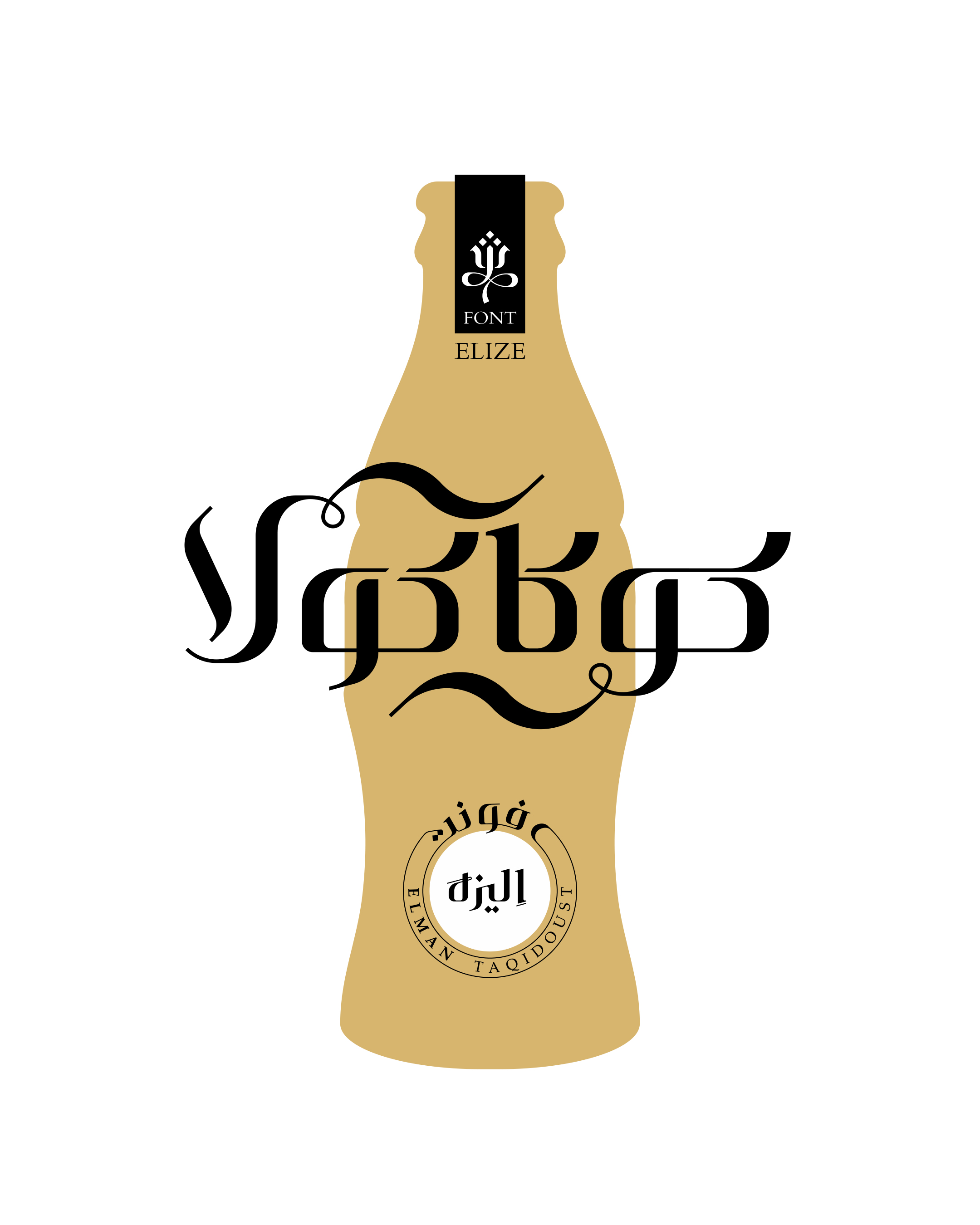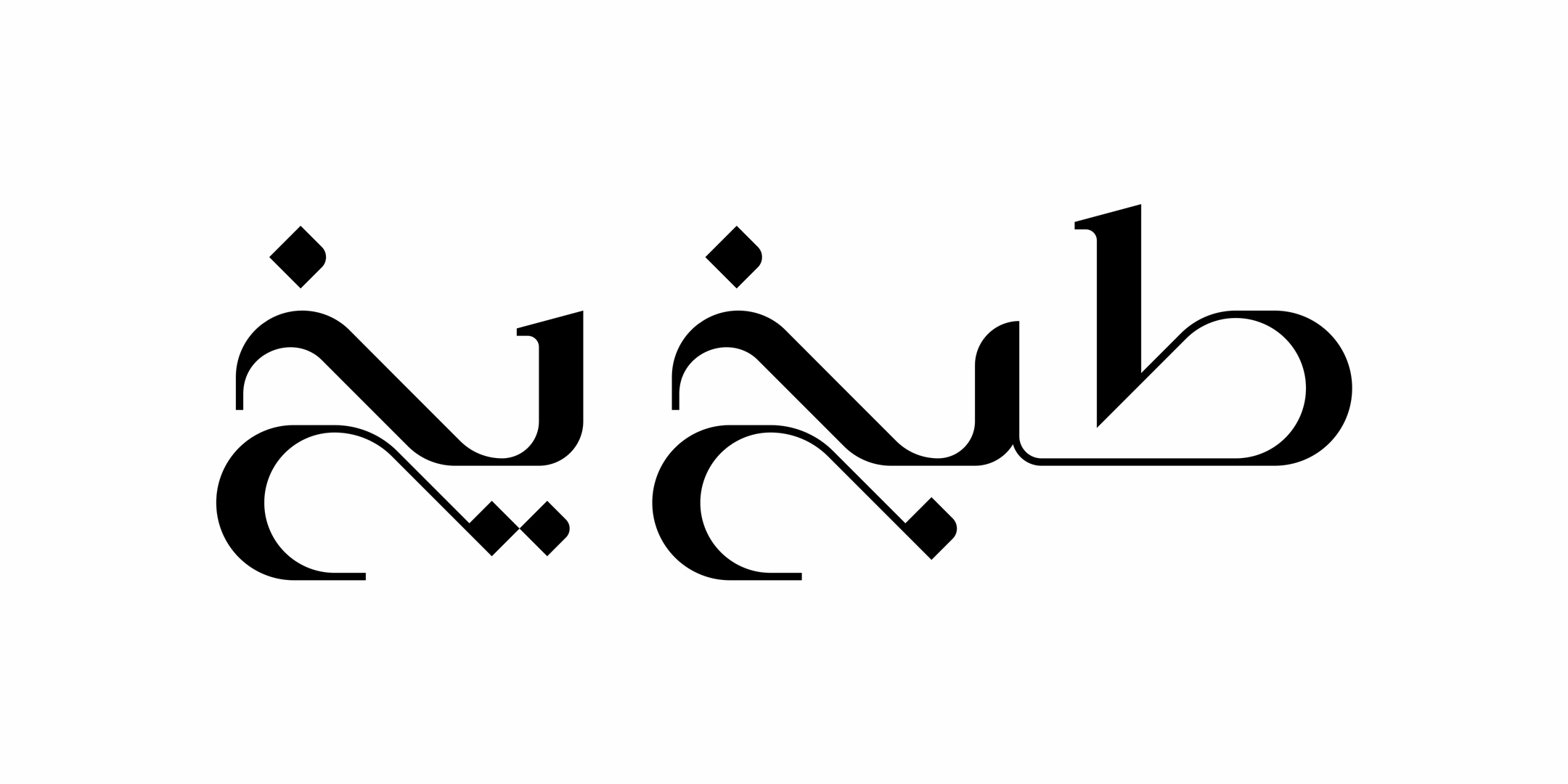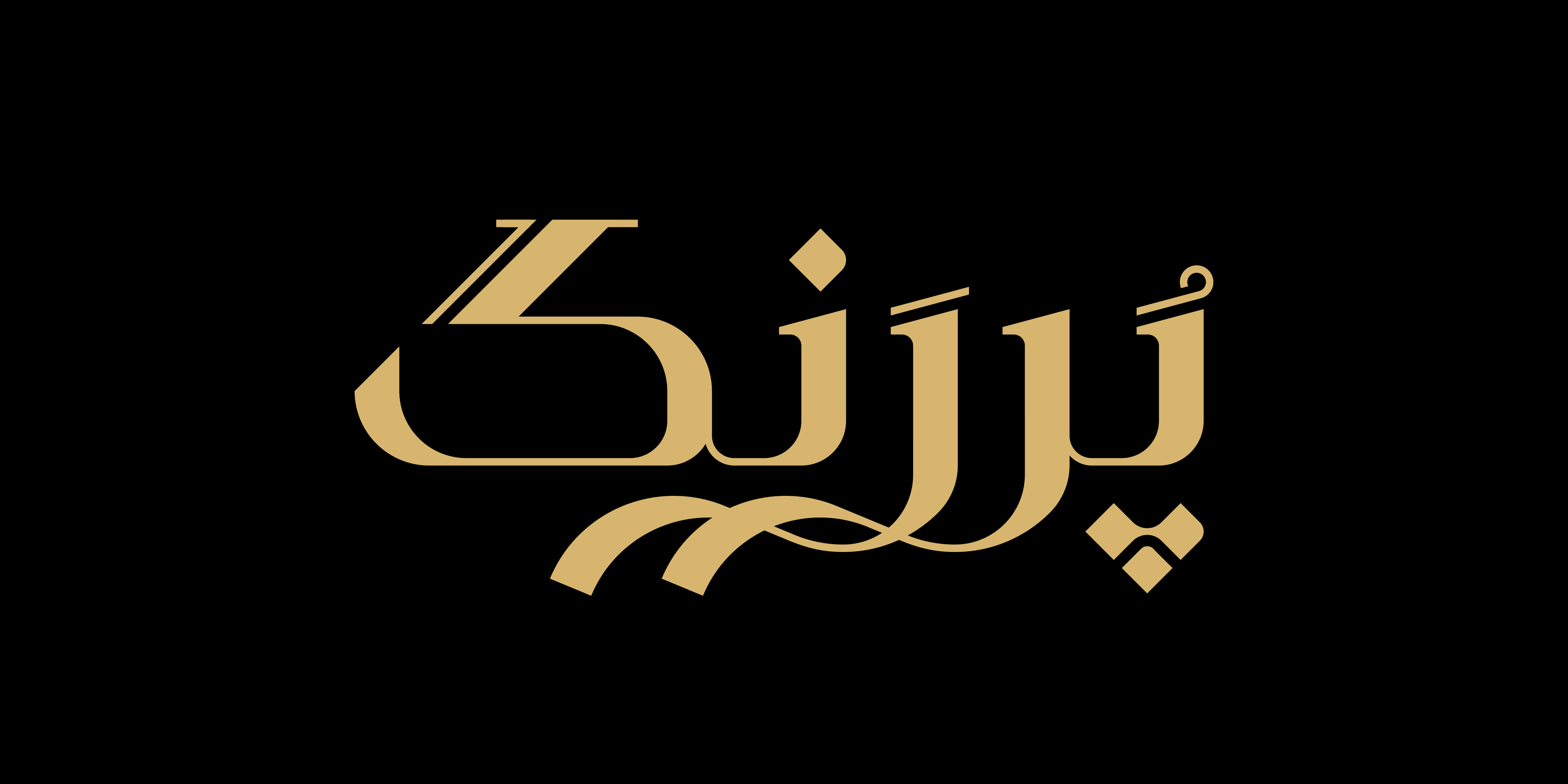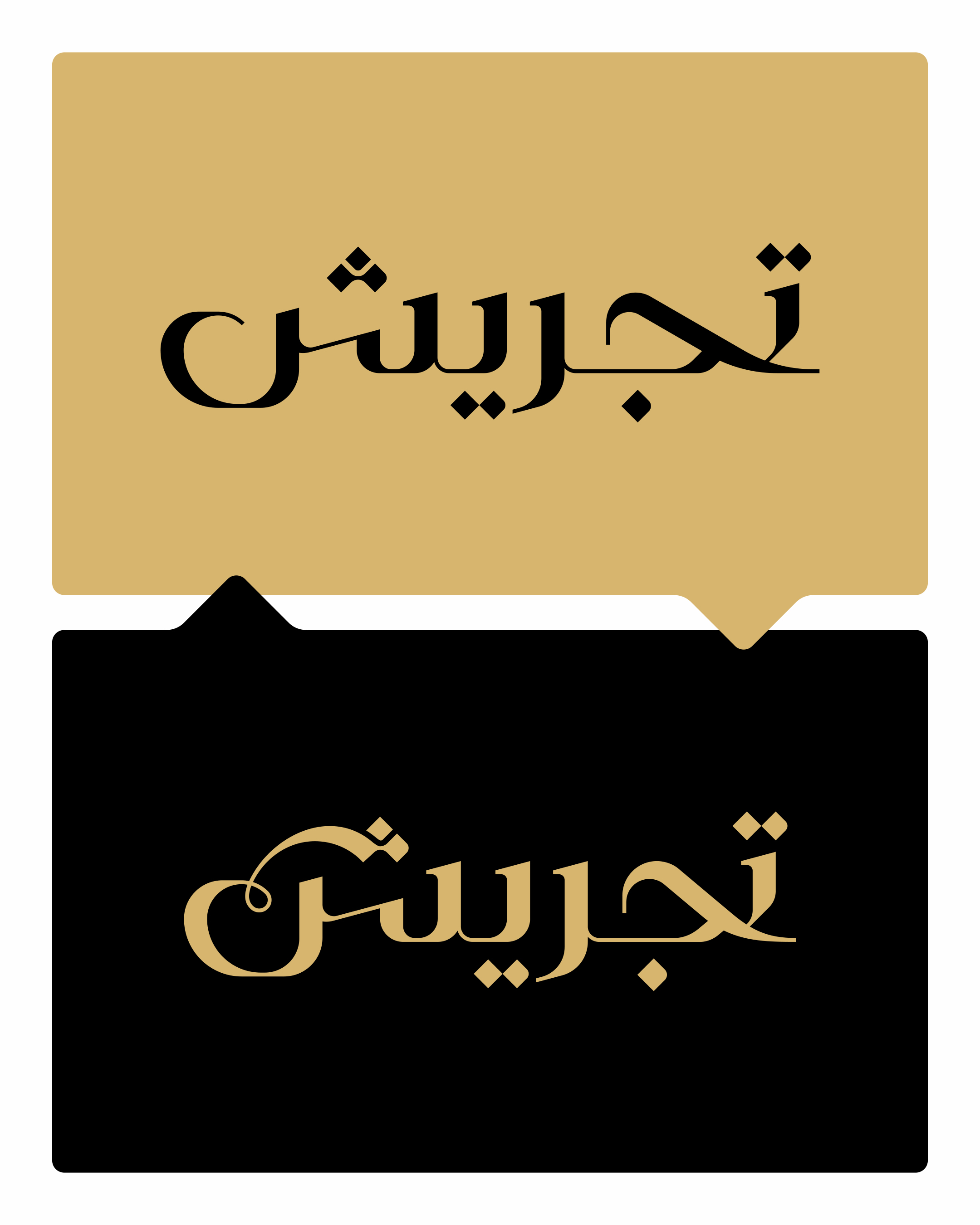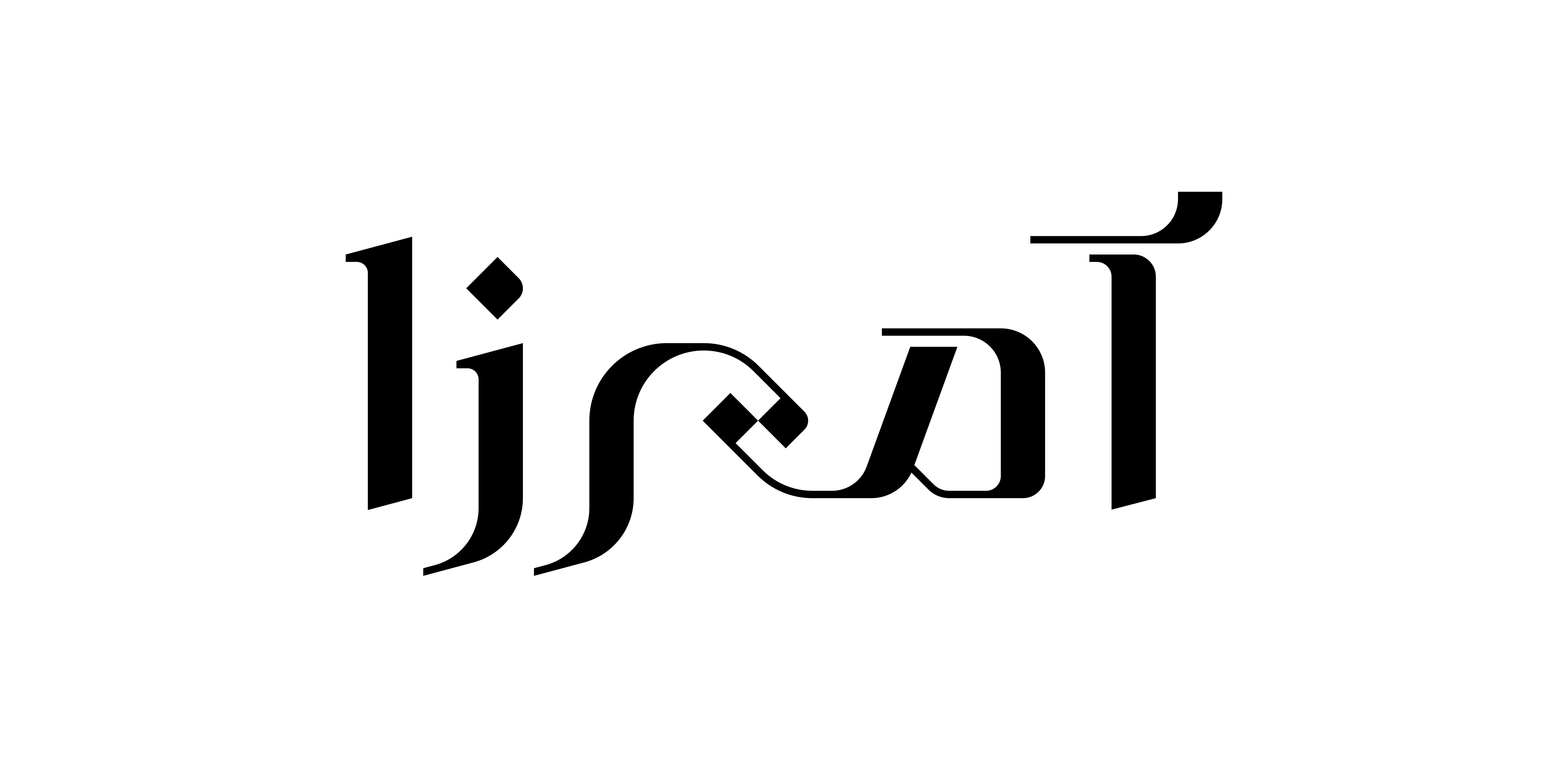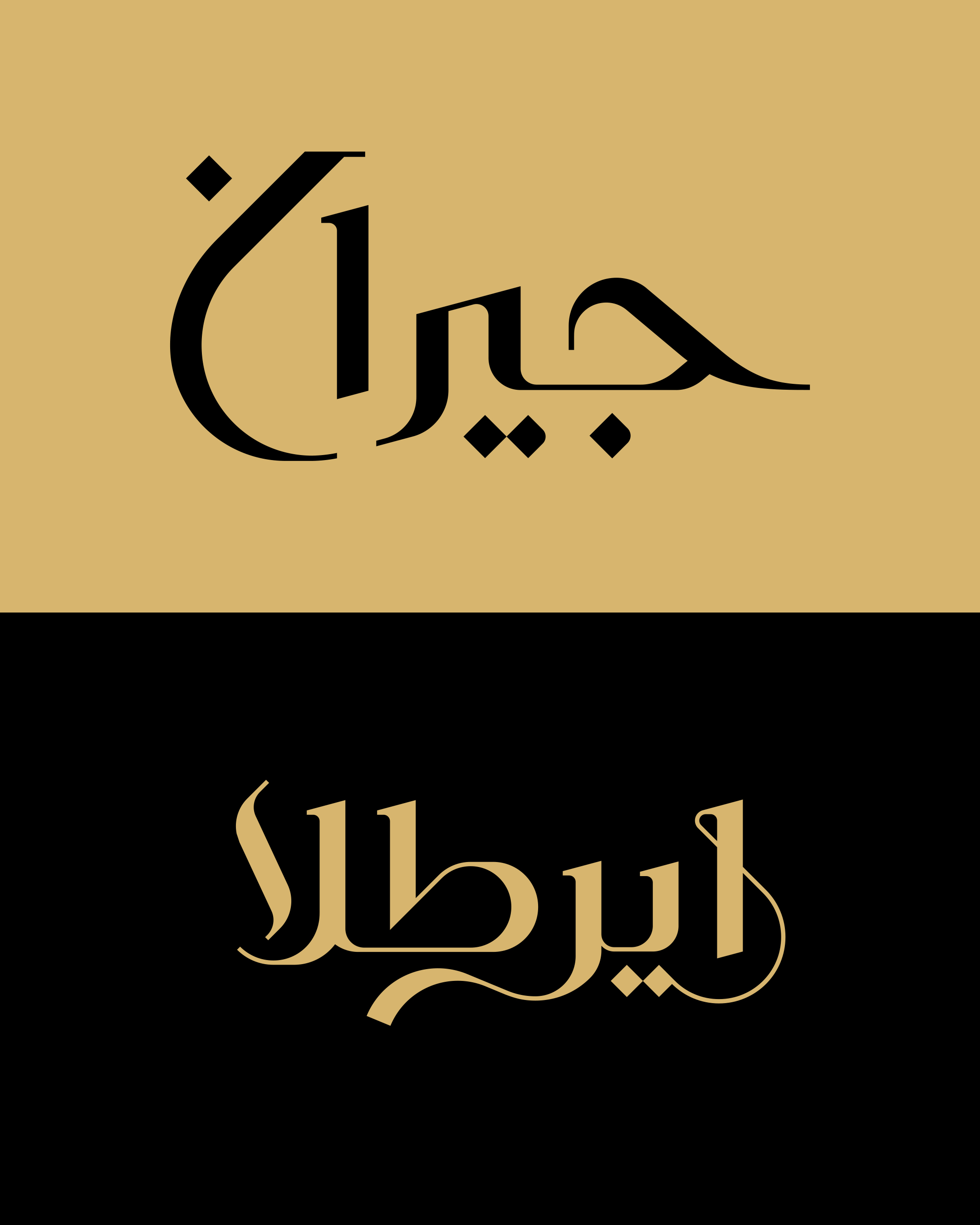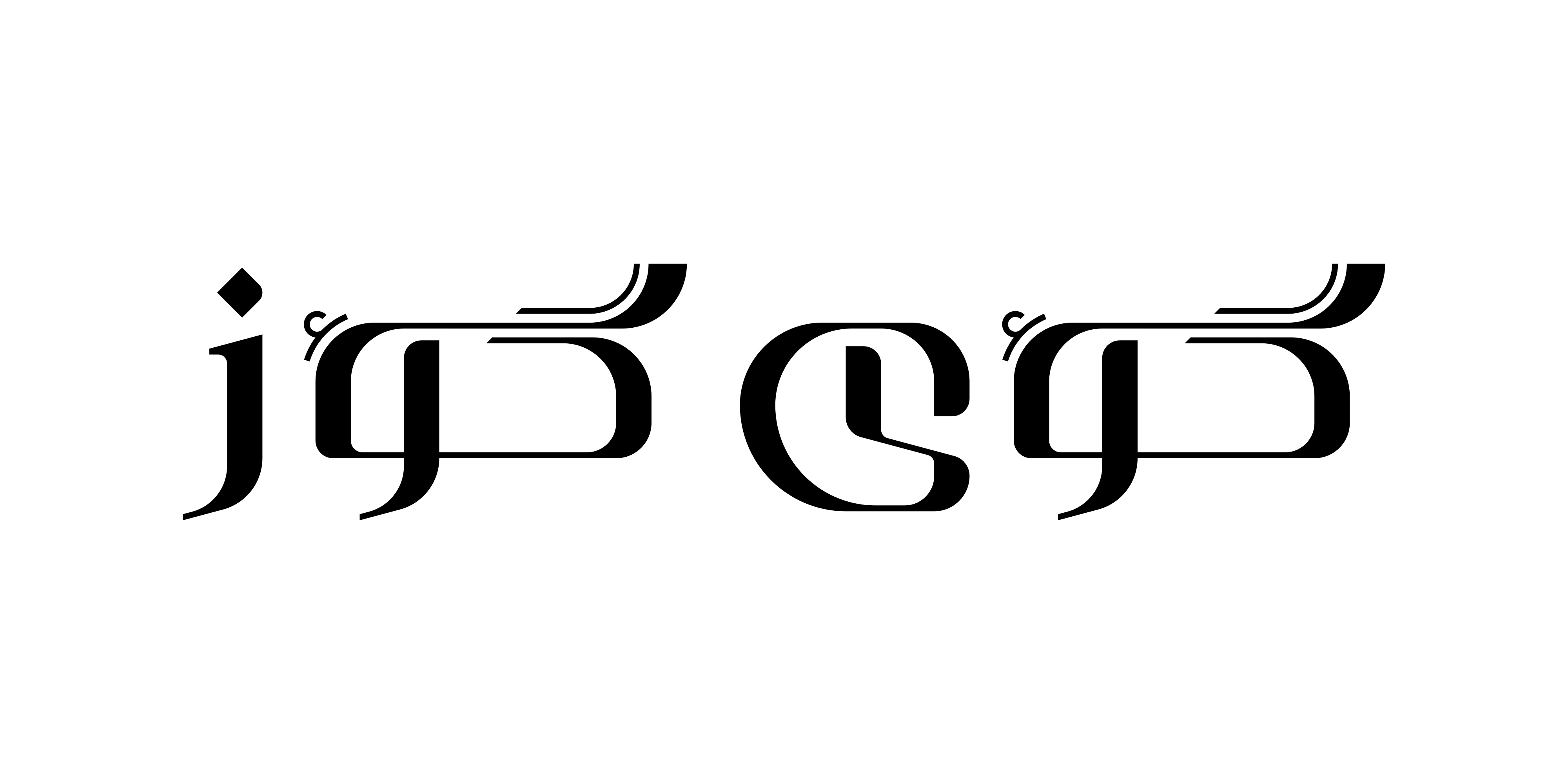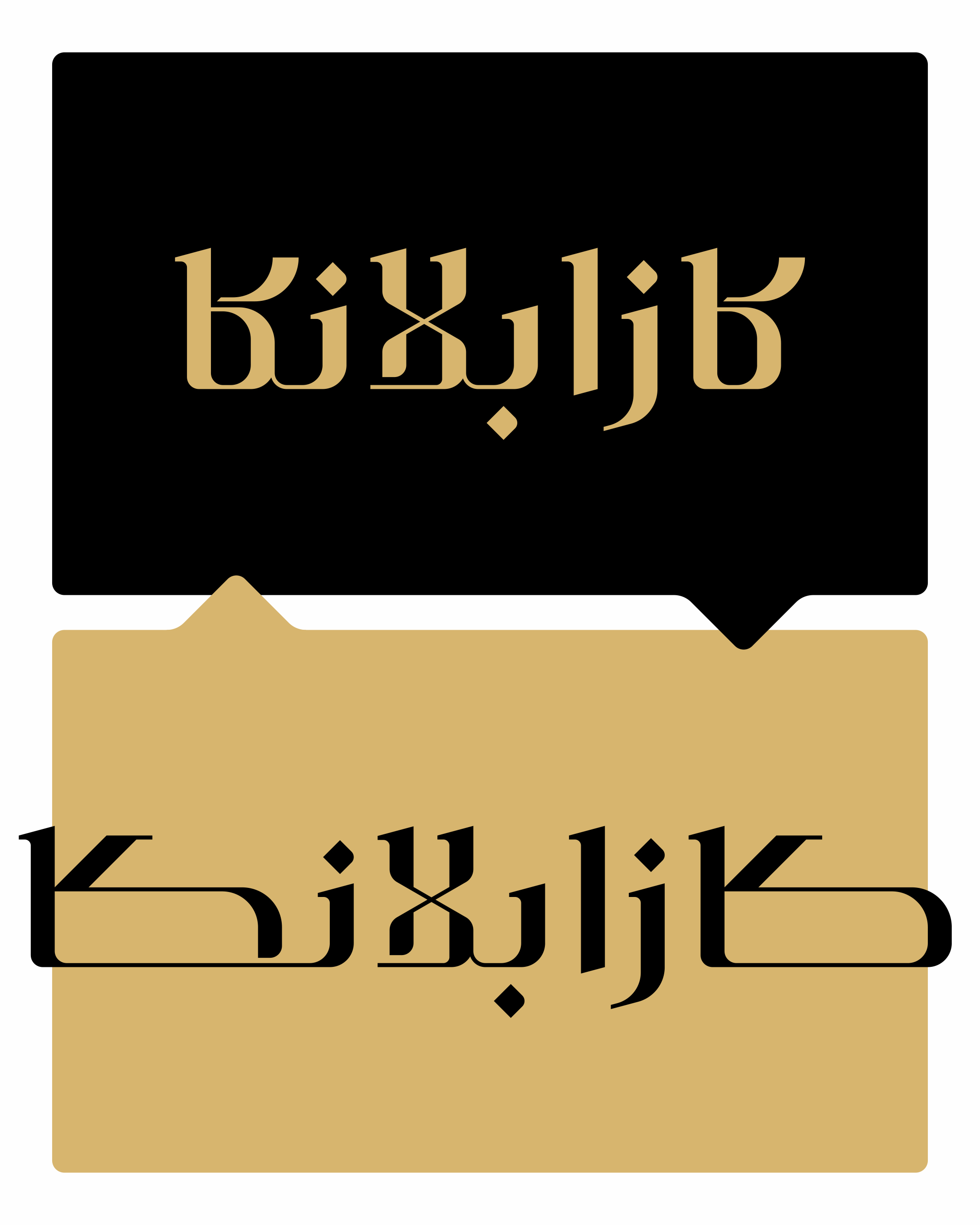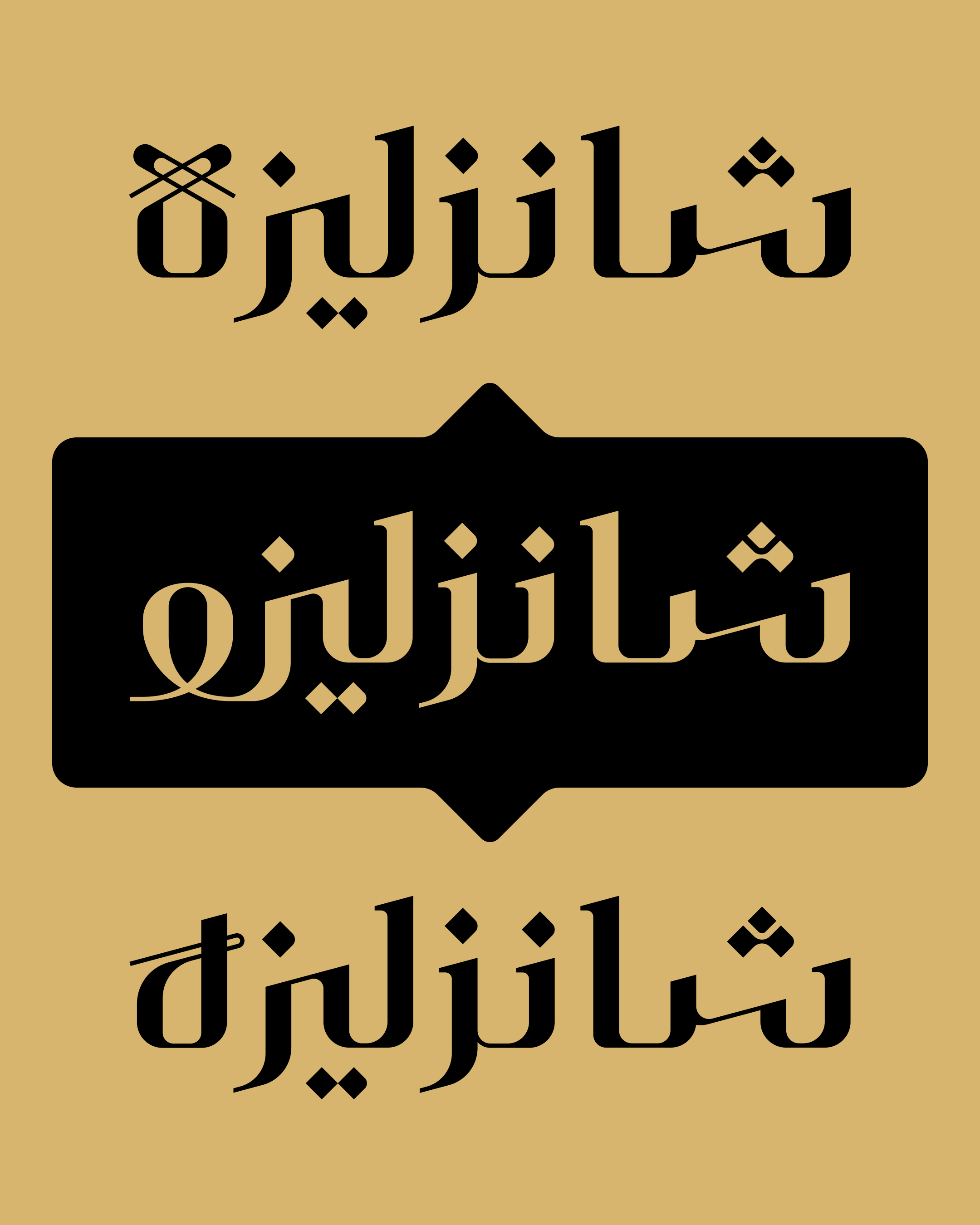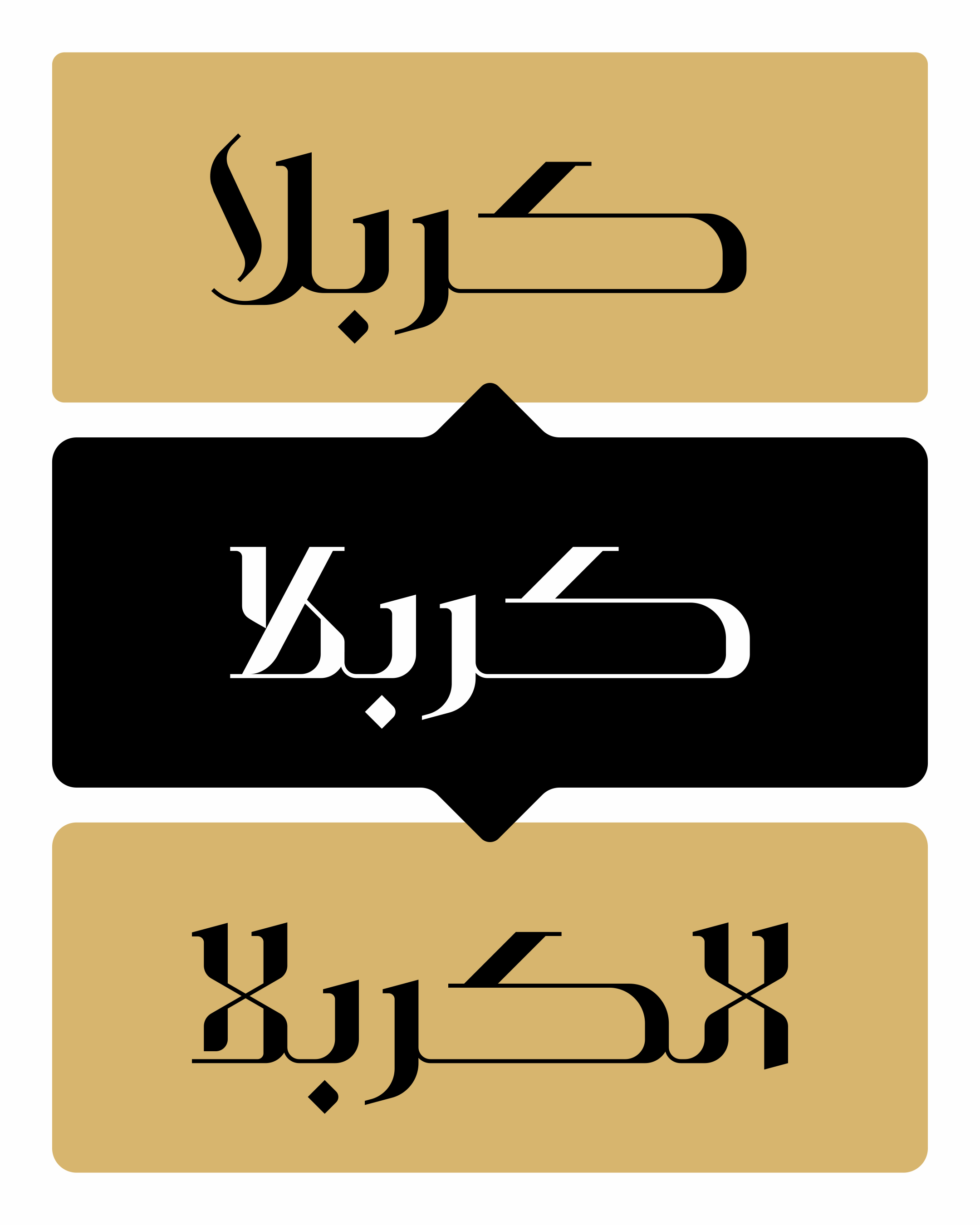
الیزه تایپفیسی لوکس و نمایشی با اتصالات هوشمند که در عین خوانایی، رفتاری غیرمنتظره و هنرمندانه دارد، انتخابی ایدهآل برای خلق لوگوتایپ، هویت بصری برندهای لوکس، صنعت مد و عناوین خاص است.
ائلمان تقیدوست طراح ارشد گرافیک و استراتژیست هویت بصری است که در حدود دو دهه بهصورت تخصصی در زمینه طراحی نشانه و تایپوگرافی مدرن فعالیت دارد. دغدغه اصلی او در سالهای فعالیتش، ارتقای استانداردهای دیزاین در پروژههای برندینگ بوده است. او از سال ۱۳۹۴ بهصورت تخصصی تمرکز خود را بر تدریس طراحی نشانه معطوف کرده و توانسته است رویکردی معاصر و ساختاریافته را در طراحی نشانه تثبیت کند.